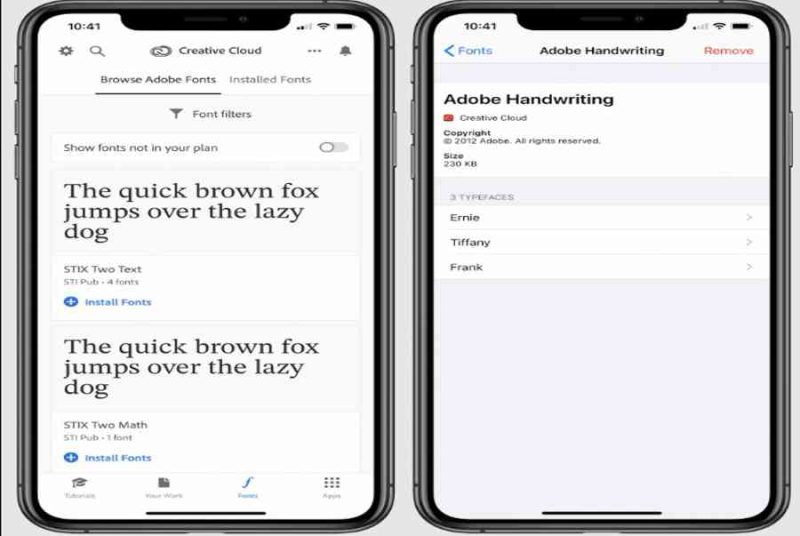
Việc cho phép sử dụng font chữ tùy chỉnh cho iPhone, iPad đã làm vui lòng những người dùng sáng tạo nội dung, giáo viên, nhà soạn văn hay những người cần sử dụng đến font chữ khác đã ao ước bấy lâu nay. Cùng GhienCongNghe điểm qua những app font chữ đẹp cho iPhone, iPad được người dùng sáng tạo nội dung hay dùng ở thời điểm đầu năm 2021.
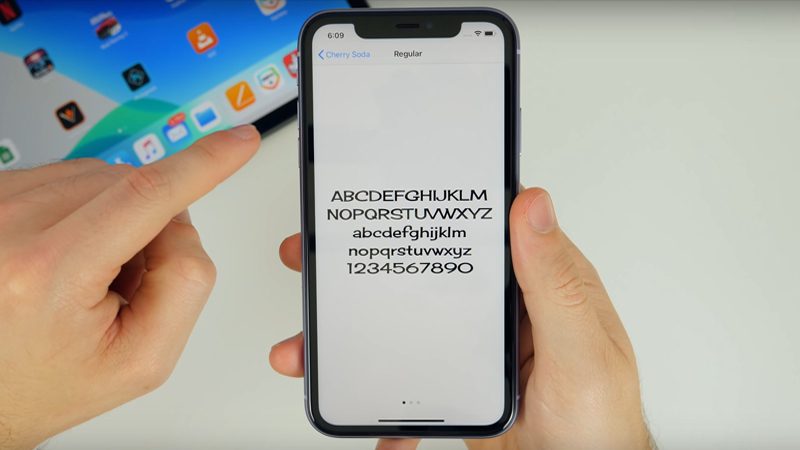
Adobe Creative Cloud app font chữ đẹp cho iPhone, iPad phổ biến nhất
Adobe Creative Cloud hoạt động giải trí với font chữ tùy chỉnh trên hàng loạt ứng dụng Adobe trên thiết bị di động của bạn, phân phối khoảng chừng 17.000 font chữ cho người ĐK Creative Cloud, 1300 font chữ trong số đó là không tính tiền. Bạn không cần phải là người ĐK dịch vụ trả phí Creative Cloud để sử dụng phông chữ không tính tiền, chỉ cần tải xuống ứng dụng và tạo một thông tin đăng nhập .Sau khi thiết lập, bạn hoàn toàn có thể nhấn vào tab Fonts ở cuối màn hình hiển thị để tải phông chữ mới trực tiếp xuống iPhone hoặc iPad và chúng sẽ có sẵn cho một những ứng dụng được tương hỗ trong cả iOS 13 và iOS 14 .
Font Diner app font chữ đẹp cho iPhone, iPad dành cho người thích hoài cổ
Font Diner là một ứng dụng không lấy phí chuyên về những font chữ chất lượng cao, mang phong thái hồi cổ cho những dự án Bất Động Sản phát minh sáng tạo trên những ứng dụng phong cách thiết kế. Có hơn 400 kiểu chữ dành cho những nhà phong cách thiết kế đồ họa ở mọi Lever. Nó cung ứng bộ phong chữ cơ bản không tính tiền và có 1 số ít bộ font bổ trợ với giá 5 đô cho mỗi bộ đó. Font Diner chỉ thích hợp với những ứng dụng Pages, Keynote và Number của Apple .
AnyFont (2$) app font chữ cho iPhone, iPad có trả phí
AnyFont được cho phép bạn thiết lập tốt bất kỳ phông chữ nào ở dạng TTF, OTF hoặc TTC trên iPhone, iPad của bạn trải qua thông số kỹ thuật. Khi setup bạn hoàn toàn có thể sử dụng những font chữ này cho Word, PowerPoint, Pages, Excel, Numbers, Keynote và những ứng dụng khác cũng sử dụng font chữ của thiết bị. Bạn hoàn toàn có thể thêm một hoặc nhiều phông chữ đồng thời dưới dạng tệp Zip hoặc tệp TTC và xem chúng trước trong ứng dụng AnyFont .
iFont app đổi font cho iPhone, iPad miễn phí tốt nhất.
Ứng dụng iFont được cho phép bạn thiết lập phông chữ mới trải qua những định dạng TTF, TTC và OTF. Bạn cũng hoàn toàn có thể thêm những tệp font chữ được nén trong tệp Zip để sử dụng cho những ứng dụng trên iPhone, iPad như Pages, Keynote, Microsoft Word hoặc bất kể ứng dụng thích hợp khác .Nó không hiển thị font chữ trên bàn phím gõ chữ hoặc những ứng dụng không thích hợp với font chữ tùy chỉnh. iFont hoạt động giải trí khá tốt với iOS 14 hoặc iPadOS 14 nên chúng tôi khuyên bạn nên tăng cấp hệ quản lý và điều hành trước khi sử dụng ứng dụng này .
RightFont (3$)
Với ứng dụng này, bạn hoàn toàn có thể setup, xem trước và quản trị phông chữ trên cả iPhone và iPad. Các định dạng OTF, TTF và TTC được tương hỗ và phông chữ hoạt động giải trí với Word, Excel, PowerPoint, Pages, Keynote, Numbers và một loạt những ứng dụng khác .Người dùng hoàn toàn có thể tải xuống font chữ trên thiết bị bằng iCloud Drive hoặc Google Drive của bạn. Nếu điều đó là không đủ, thậm chí còn hoàn toàn có thể mở và setup phông chữ nhận được qua AirDrop hoặc trải qua email. Ngoài ra, RightFont trọn vẹn thích hợp với iOS 14 và được cho phép bạn xem trước tổng thể những họ phông chữ với nội dung tùy chỉnh hàng loạt .